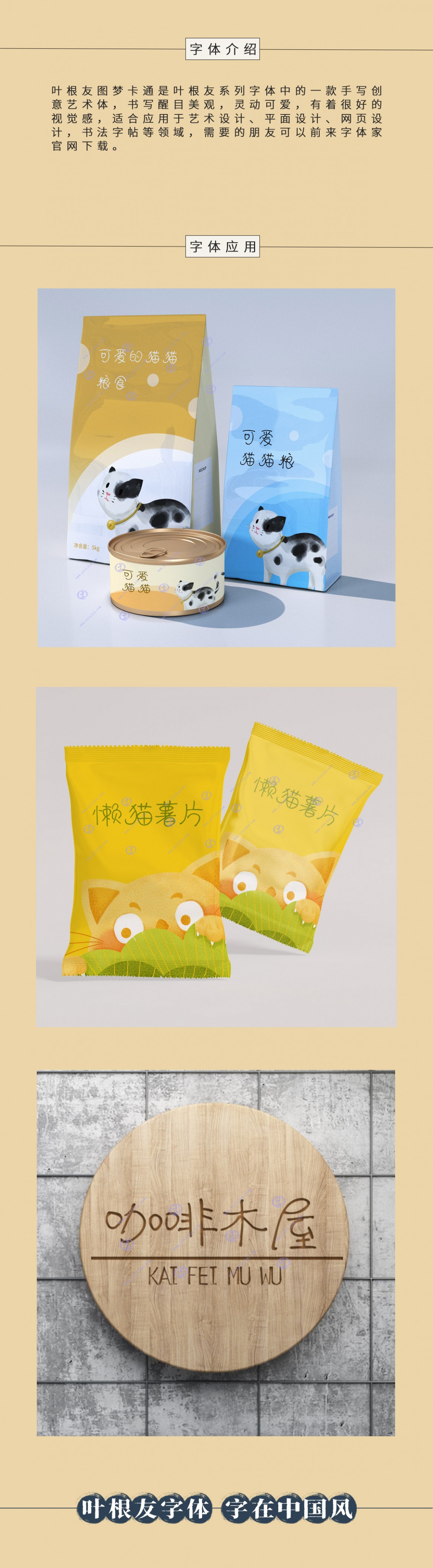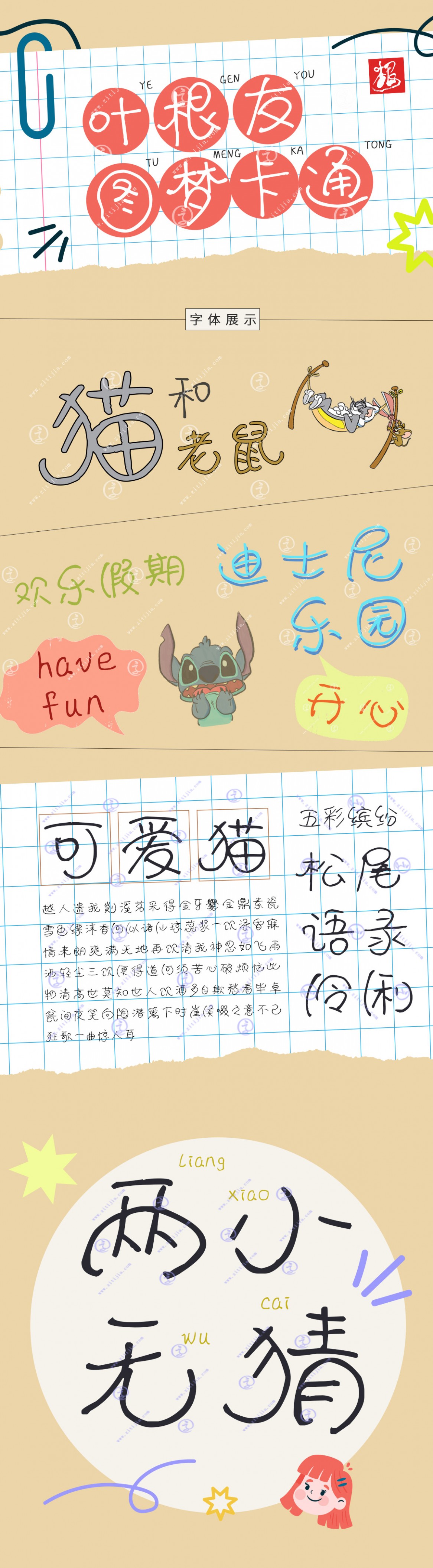
葉根友圖夢卡通
葉根友圖夢卡通是葉根友系列字體中的一款手寫創(chuàng)意藝術(shù)體,書寫醒目美觀,靈動可愛,有著很好的視覺感,適合應(yīng)用于藝術(shù)設(shè)計、平面宣傳設(shè)計、網(wǎng)頁設(shè)計,書法字帖等領(lǐng)域,需要的朋友可以前來字體家官網(wǎng)下載。